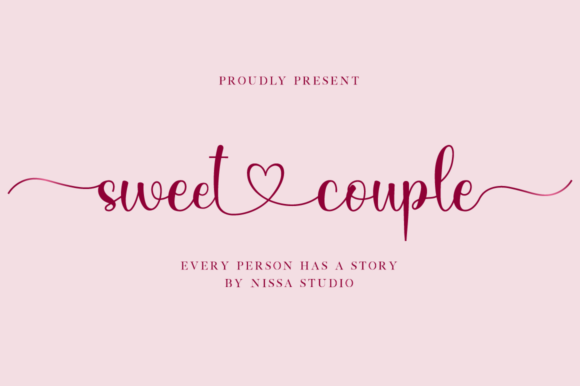
Sweet Couple
Sweet Coupleのような高品質の素材をお探しの場合、このプレミアムパッケージはクリエイティブなプロジェクトに素晴らしい選択です。
POD(オンデマンド印刷)製品、結婚式の招待状、またはソーシャルメディアのグラフィックを作成している場合でも、Sweet Coupleは理想的です。